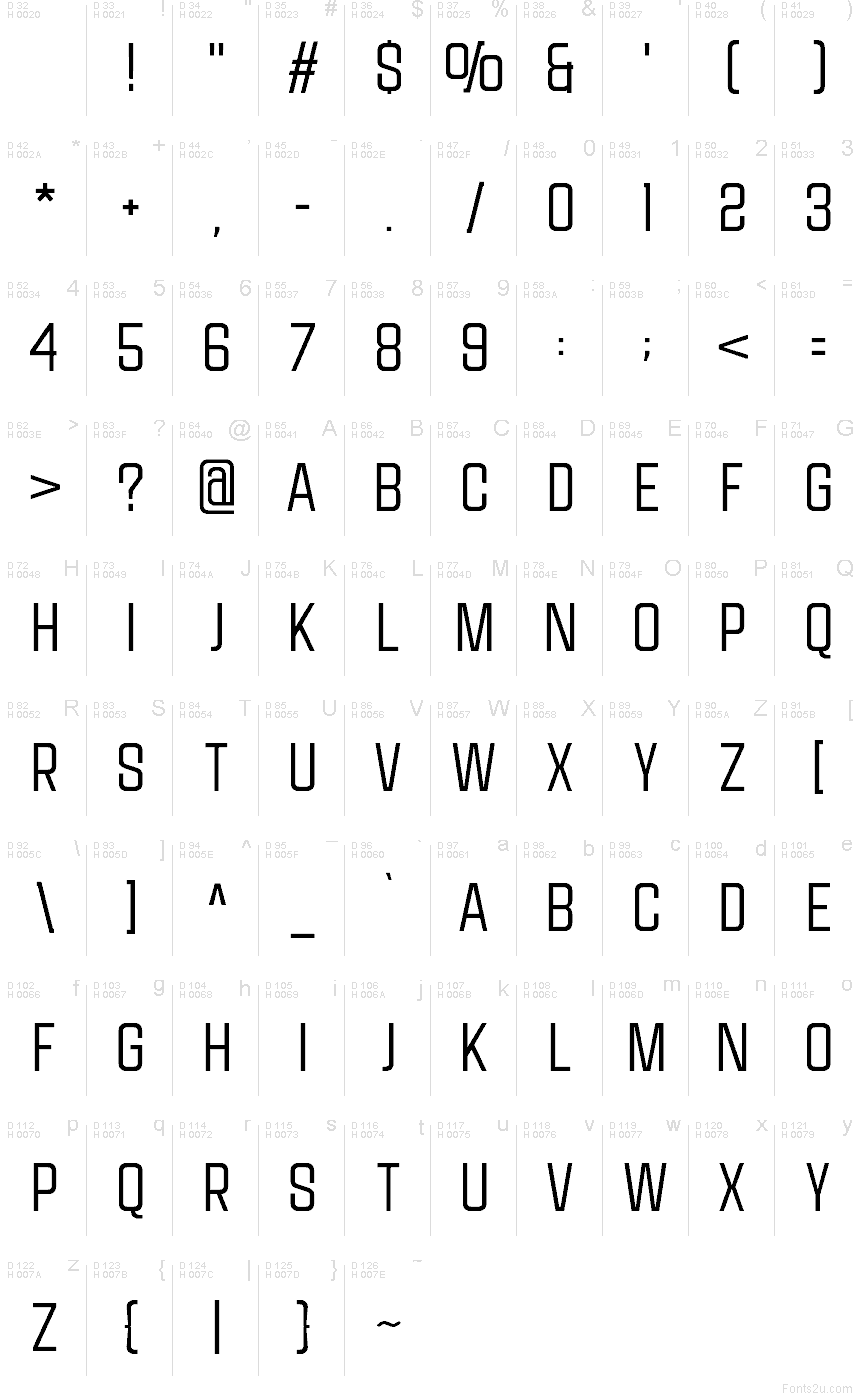
Muckley de Ari Juanda es una tipografía sans serif condensada y gratuita con una estructura austera y modernista. Sus letras altas y estrechas presentan trazos en su mayoría uniformes y curvas rigurosamente controladas. Las esquinas redondeadas suavizan una construcción que, de otro modo, resultaría angulosa.
Su modernismo industrial resulta adecuado para señalética direccional y carteles de exposiciones contemporáneas. Posee una franqueza nítida y de precisión mecánica. En el diseño editorial, su silueta estrecha permite componer portadas de revistas contundentes y aperturas de sección despejadas.